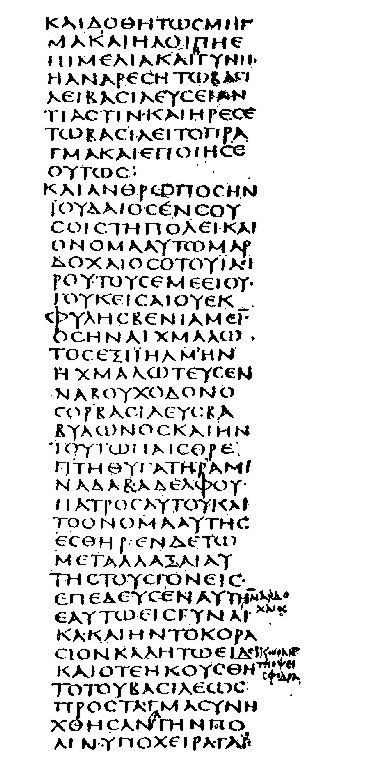
Codex SinaiticusTambém conhecido como «Manuscrito Aleph» (primeiro algarismo do alfabeto hebraico), é um dos mais importantes manuscritos gregos já descobertos, pois além de ser um dos mais antigos (século IV), e o único codex que contém o Novo Testamento inteiro.Foi elaborado com letras unciais. Actualmente acha-se no Museu Britânico. Juntamente com o Codex Vaticanus, é um dos mais importantes manuscritos gregos para o Criticismo Textual, além do texto da Septuaginta. O Codex Sinaiticus foi descoberto por Constantin von Tischendorf, na sua terceira visita ao Mosteiro Ortodoxo de Santa Catarina, no sopé do Monte Sinai, em 1859. Nas duas primeiras viagens, ele conseguiu obter partes do Antigo Testamento, encontrados num cesto que continha pedaços de vários manuscritos. Tischendorf teria ouvido de um bibliotecário que aqueles manuscritos eram lixo, e que seriam queimados no forno do mosteiro. O czar da Rússia Alexandre II enviou-o para procurar os demais manuscritos, dos quais ele estava convencido de que estariam no próprio mosteiro. A história de como Tischendorf localizou o manuscrito, que continha a maioria do Antigo Testamento e todo o Novo Testamento, tem o drama de um romance. O czar da Rússia enviou 9000 rublos ao mosteiro como compensação pelo manuscrito. Existem algumas controvérsias que envolvem a transferência deste manuscrito para a Rússia. Bruce Metzger, um investigador do Novo Testamento escreve: "Certos aspectos das negociações que levaram à transferência do codex para a posse do Czar estão abertos a interpretações diversas, mas a história reflete a franqueza de Tischendorf e a boa fé dos monges do mosteiro de Santa Catarina". Durante muitas décadas, foi conservado na Biblioteca Nacional da Rússia. No dia de Natal de 1933, a então União Soviética vendeu o Codex à Biblioteca Britânica pela incrível soma de apenas £100,000 (libras esterlinas). Em Maio de 1975, durante um trabalho de restauração, os monges do mosteiro de Santa Catarina descobriram um cômodo em baixo da capela de São Jorge e, neste local, uma grande quantidade de fragmentos de pergaminho. Entre estes fragmentos, foram achadas doze cópias perdidas do Antigo Testamento do Codex Sinaiticus.